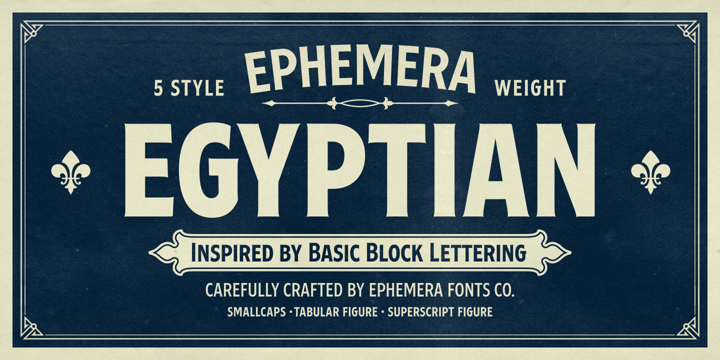
Египетские шрифты: что это такое и некоторые из лучших шрифтов
Когда мы говорим о шрифтах, мы также говорим о буквах, которые переносят нас в отдаленные места и времена нашей истории и эволюции. Есть шрифты, высеченные в камне, которые на протяжении многих лет были первым дизайнерским механизмом в шрифтах. Со временем эти шрифты стали тем, что сейчас занимает много места вокруг нас, — римскими шрифтами.
Но в этом посте мы не будем говорить об этом стиле, а познакомим вас с другой эпохой, когда было много бума и силы. Время, полное фараонов и пирамид, где все жили вместе, египетских купелей.
Именно по этой причине мы собираемся объяснить, что они собой представляют, для чего они используются, когда мы говорим о дизайне, и какие функции они выполняют, когда мы с ними взаимодействуем.
что такое египетские шрифты
Египетские шрифты — это один из стилей, которые являются частью различных существующих типографских семейств и стилей. Они получили название египетских, хотя также известны как мекканские шрифты.. Что характеризует этот стиль, так это то, что они сохраняют характеристики, аналогичные римским шрифтам, из-за наличия засечек в их формах. Их часто путают с ними, поскольку они также встречаются в местах для чтения или в журналах, таких как некоторые заголовки, поэтому их очень часто можно увидеть в нашей повседневной жизни.
Кроме того, его поразительная форма привлекла внимание многих брендов и компаний.
Например, есть такие бренды, как El País, Sony или Honda. которые присоединились к включению этого типа букв в свои логотипы. Короче говоря, это шрифты, которые поддерживают классический и скромный стиль римской семьи, но в то же время они очень привлекательны, поскольку их форма всегда сохранялась как своего рода отпечаток или штамп.
общие черты
Египетские шрифты в основном характеризуются за то, что содержит в своих формах однородные модуляции, то есть с первого взгляда нельзя оценить контраст в его формах.- Что похоже на римские шрифты, так это то, что они сохраняют богато украшенные и очень заметные засечки в своих формах, а это означает, что, как мы указывали ранее, поддерживать этот классический и серьезный стиль того времени.
- Штрихи и их общий вид довольно однородны, то есть, есть штрихи, которые различаются и не следуют одному и тому же шаблону, Это не означает, что они плохо проработаны, а скорее то, что для сохранения коннотаций эпохи, из которой они происходят, было необходимо разработать собственную графическую линию, обозначающую чистый образ египетской эпохи.
- Тот факт, что они содержат такие отмеченные окончания, делает его одним из шрифтов, подходящих для использования в заголовках или больших текстах, где главный герой, несомненно, является шрифтом. Именно по этой причине, как мы уже указывали ранее, он использовался во многих логотипах некоторых из наиболее представительных брендов. Короче говоря, это идеальная типографика, если вы также посвятите себя дизайну айдентики.
Типологии
Есть два стиля египетских шрифтов, которые сохраняют разные характеристики. Каждый из стилей функционален, и мы можем найти их в разных приложениях и целях. Именно поэтому, чтобы вы лучше понимали, о чем мы говорим, мы обобщили его характеристики и, кроме того, также собираемся объяснить, что это за функции, которые они выполняют в сфере дизайна.
мягкая ссылка
Когда мы говорим о гуманизме, мы имеем в виду, что его штрихи намного лучше определены и его внешний вид гораздо менее визуально перегружен.В отличие от обычных, этот стиль сохраняет свои модуляции полностью видимыми, что означает, что штрихи не становятся полностью однородными. Кроме того, они поддерживают гораздо менее жесткую точку соединения, то есть каждый из кадров, из которых сделан шрифт, менее форсирован и остается более незамеченным.
Это, несомненно, один из стилей, который лучше всего используется, поскольку он демонстрирует небольшое меньшинство силы в своих формах и графической линии. Среди его наиболее известных шрифтов: Claredon и Lino Letter.
жесткая ссылка
Египетские шрифты с жесткой связью отказываются от римского классического и четко определенного гуманистического стиля и обращаются к гораздо более геометрическому стилю. Геометрические шрифты — это обычно те, которые мы знаем как шрифты без засечек. Поэтому, как следует из названия, будучи геометрическими шрифтами, они весьма поразительны из-за большого диапазона баланса, который они содержат.
Модуляция этих форм снова однородна, а последние штрихи снова отмечены и хорошо видны. Некоторые из самых выдающихся шрифтов этого стиля: Rockwell и Memphis.
Использование и применение египетских шрифтов